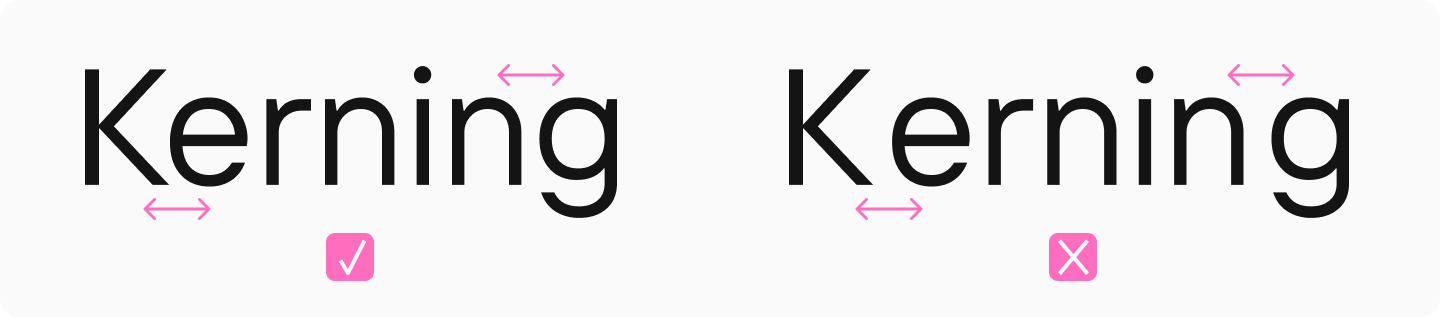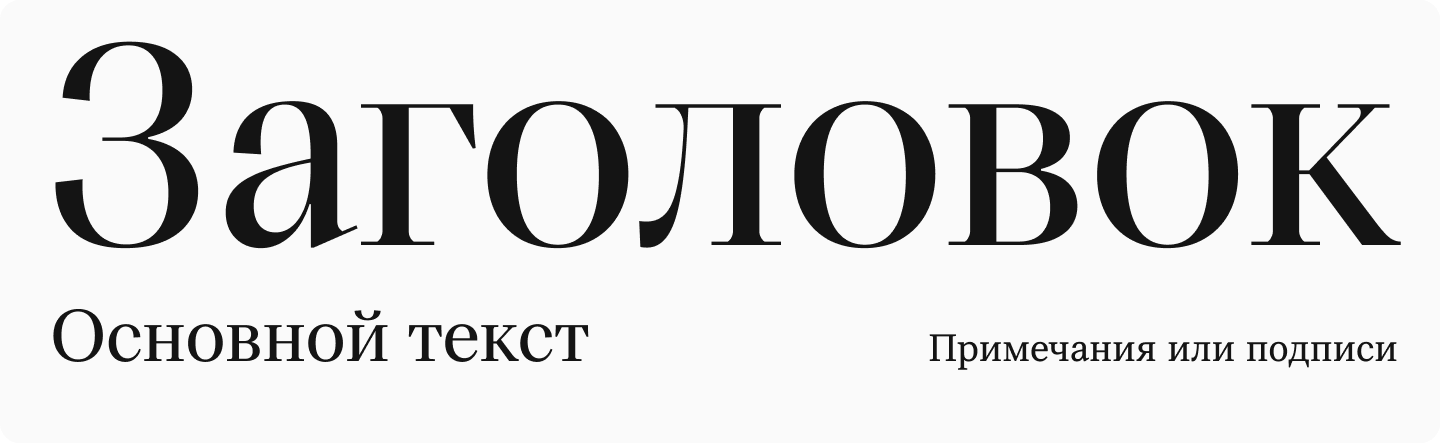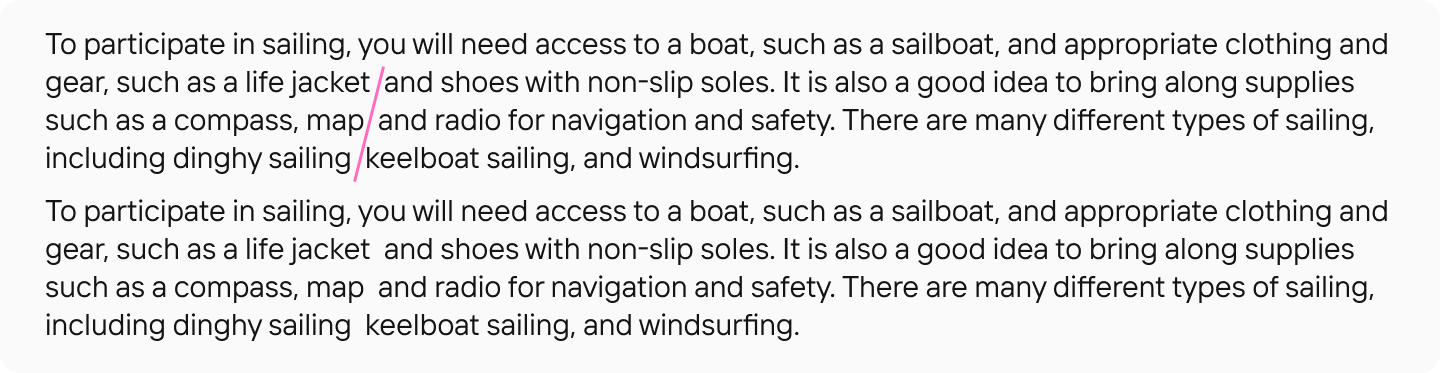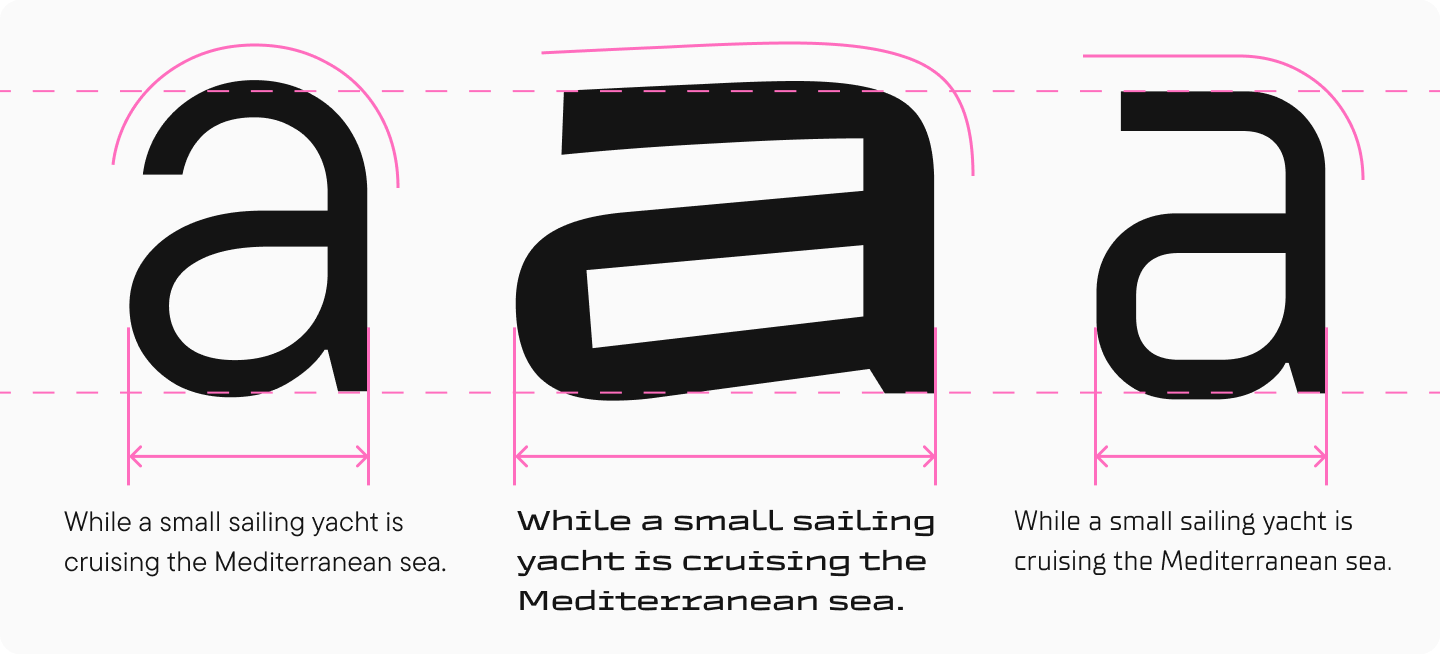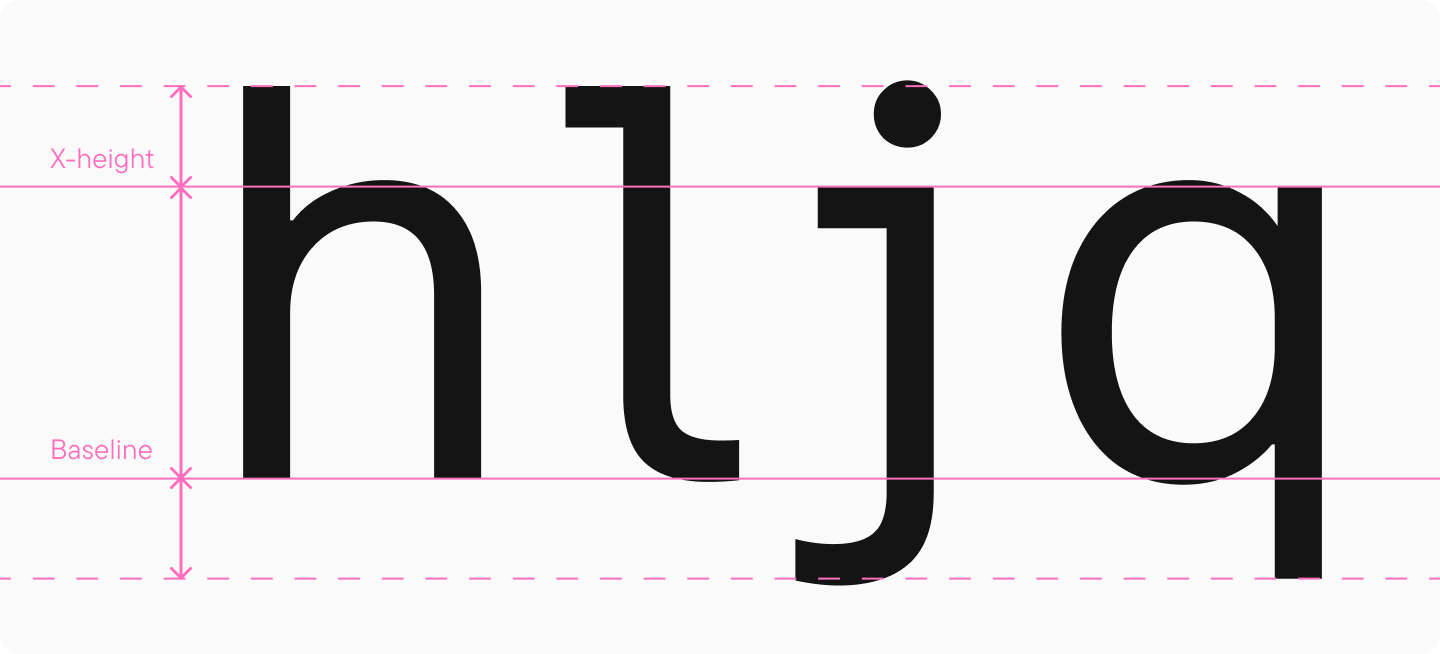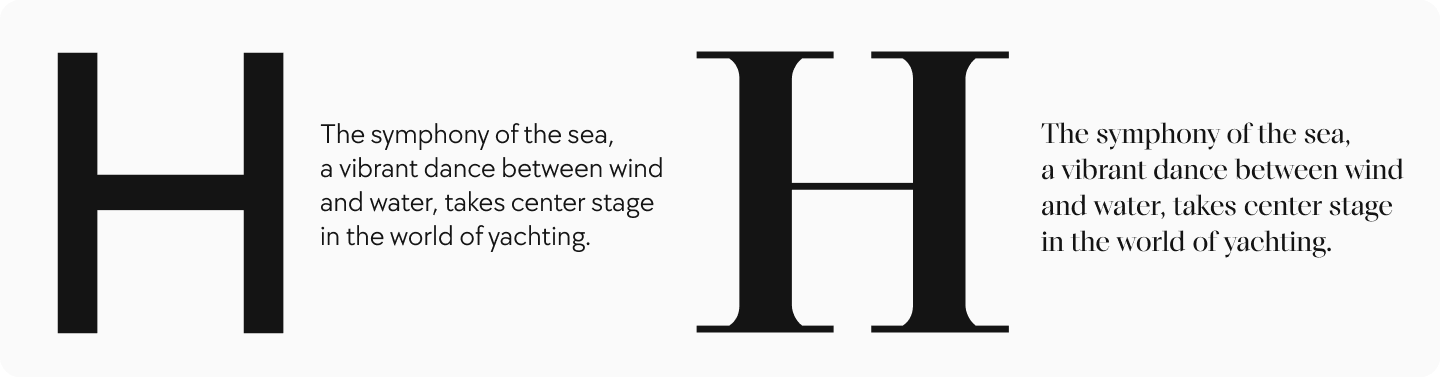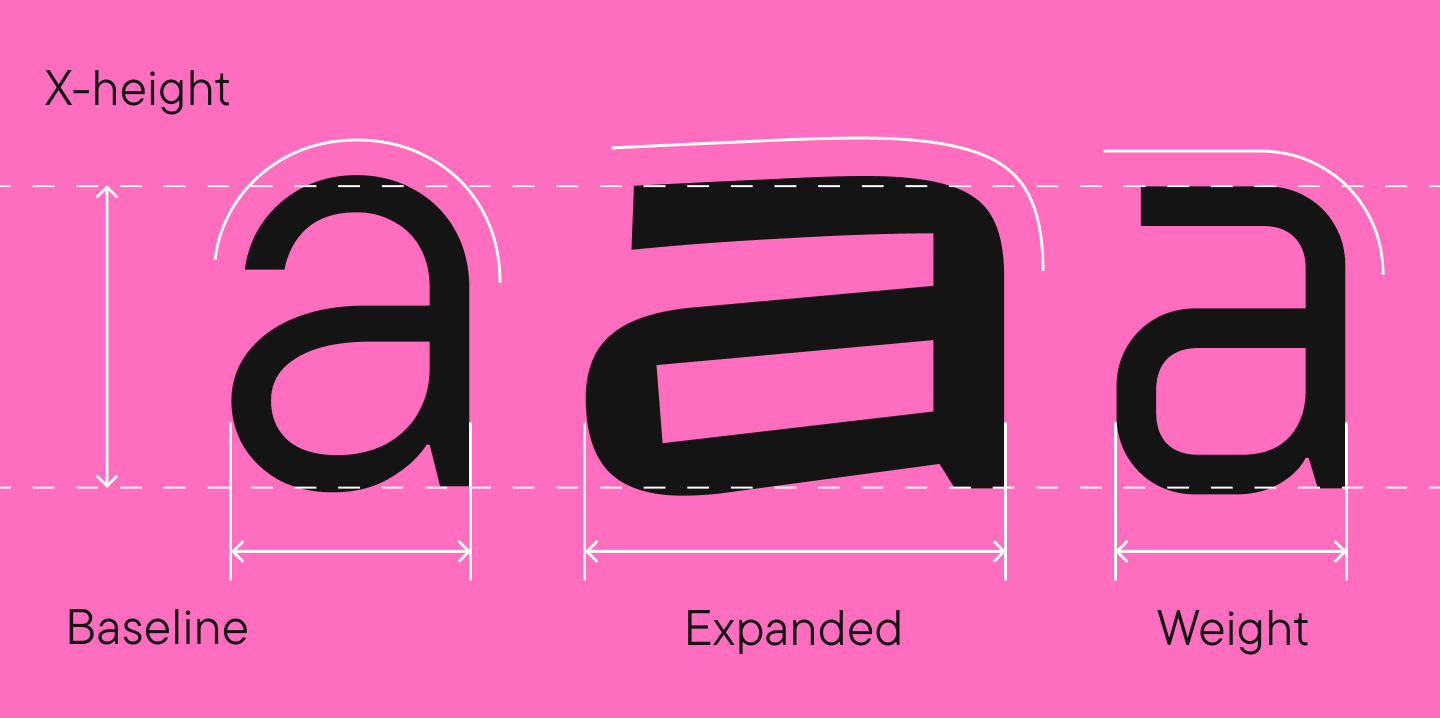
Разборчивость и удобочитаемость: в чём разница?
В этой статье мы разберёмся, что такое удобочитаемость и разборчивость и в чём разница между ними, каким должен быть разборчивый шрифт и от чего зависит читабельность текста.
Что такое разборчивость?
Определение разборчивости (англ. legibility) следующее: это различимость отдельных символов, лёгкость их распознавания. Если шрифт разборчивый, вы без труда отличите друг от друга похожие по форме символы даже в мелком тексте. Например, не перепутаете «а» с «о» или «г» с «т».
Что такое удобочитаемость?
Удобочитаемость, читабельность или читаемость (англ. readability) чаще всего употребляются как синонимы. Определение у этих терминов в данном контексте одно — лёгкость восприятия не отдельных букв, а всего текста целиком. Удобочитаемость шрифта определяется тем, насколько читателю удобно и легко «скользить» по строкам текста, не отвлекаясь и не «спотыкаясь». Разборчивость — одна из составляющих удобочитаемости.
Составляющие читаемости и разборчивости
Факторы, влияющие на разборчивость, в основном связаны с рисунком самих знаков: их формой, пропорциями, шириной и деталями. Чем чётче и проще очертания букв, тем выше разборчивость.
Читабельность же зависит не только от формы букв, но и от того, как знаки взаимодействуют между собой. Сюда входят такие факторы, как межстрочный и межбуквенный интервал, размер шрифта и многое другое.
Важно учитывать, что шрифт может быть разборчивым, но при этом неудобным для чтения больших массивов текста — и наоборот. Ниже мы подробнее рассмотрим факторы, влияющие на разборчивость и читабельность.
Как заставить типографику работать на улучшение опыта чтения
Чтобы типографика работала в интересах пользователя, нужно подходить к выбору шрифта и оформлению текста комплексно. На первом этапе стоит обеспечить базовую разборчивость, выбрав подходящий шрифт, а затем проверить его удобочитаемость и настроить дополнительные параметры.
Как повысить разборчивость вашего шрифта (или выбрать разборчивый шрифт)?
Высота по оси X
Высота по оси X, или Х—height — это заданный в шрифте параметр высоты строчных букв относительно прописных; линия роста строчных знаков без учёта свисаний. Исследования показывают, что этот параметр, как и длина верхних и нижних выносных элементов, напрямую влияют на разборчивость шрифта.
Так, буквы с выносными элементами, такие как «b» или «p», распознаются легче, чем те, у которых их нет. Увеличение длины этих элементов улучшает распознавание для ряда букв. А увеличение высоты букв по оси Х положительно влияет на распознавание всех символов.
Соответственно, чтобы получить разборчивый текст, стоит выбирать шрифт с большей Х—height.
Вес
Вес — это толщина штрихов или жирность символов. Этот параметр влияет как на разборчивость отдельных символов, так и на общую читабельность.
Лучше всего читаются средние по весу начертания — то есть регулярные или базовые. Слишком тонкие линии будут теряться, а слишком жирные — «слипаться» в плотную массу, мешая разборчивости отдельных символов.
Контраст штрихов
Контраст — это соотношение толщин основных и дополнительных штрихов в шрифте. Шрифт может быть неконтрастным, малоконтрастным, контрастным и сверхконтрастным.
Наиболее разборчивые и хорошо читаемые шрифты — неконтрастные и малоконтрастные. Контрастные и сверхконтрастные шрифты могут быть неразборчивы, особенно в маленьком кегле, так как тонкие штрихи могут теряться.
Ширина
Узкие или широкие шрифты могут стать интересным дизайнерским решением, однако они хорошо подходят для акциденции, а не для использования в текстовом наборе. Зауженные или расширенные пропорции будут мешать и разборчивости, и удобочитаемости. Поэтому для повышения читабельности текста выбирайте шрифты со стандартными пропорциями.
Апертура
Апертура — это степень открытости знака. Например, если у буквы «С» маленькое расстояние между верхним и нижним терминалом — это закрытая апертура, а если большое — это открытая апертура. Как показывают исследования, закрытые апертуры распознаются хуже, в то время как открытые апертуры способствуют большей разборчивости и, следовательно, общей читаемости.
Дисплейные и текстовые шрифты
Шрифты по назначению можно разделить на акцидентные и текстовые.
Акцидентные, или дисплейные шрифты обладают ярким, выразительным характером и часто выглядят необычно. Они предназначены для привлечения внимания и используются в акцентных надписях и заголовках, поэтому их нередко называют заголовочными. Часто акцидентные шрифты насыщены множеством декоративных элементов, которые эффектно выглядят в большом кегле, но теряются в малом размере, затрудняя воспр 1f40 иятие текста. Также им обычно присущ высокий контраст: он усиливает выразительность, но ухудшает читаемость при небольшом размере. Такие шрифты хорошо смотрятся в крупных надписях, но не подходят для длинных текстов.